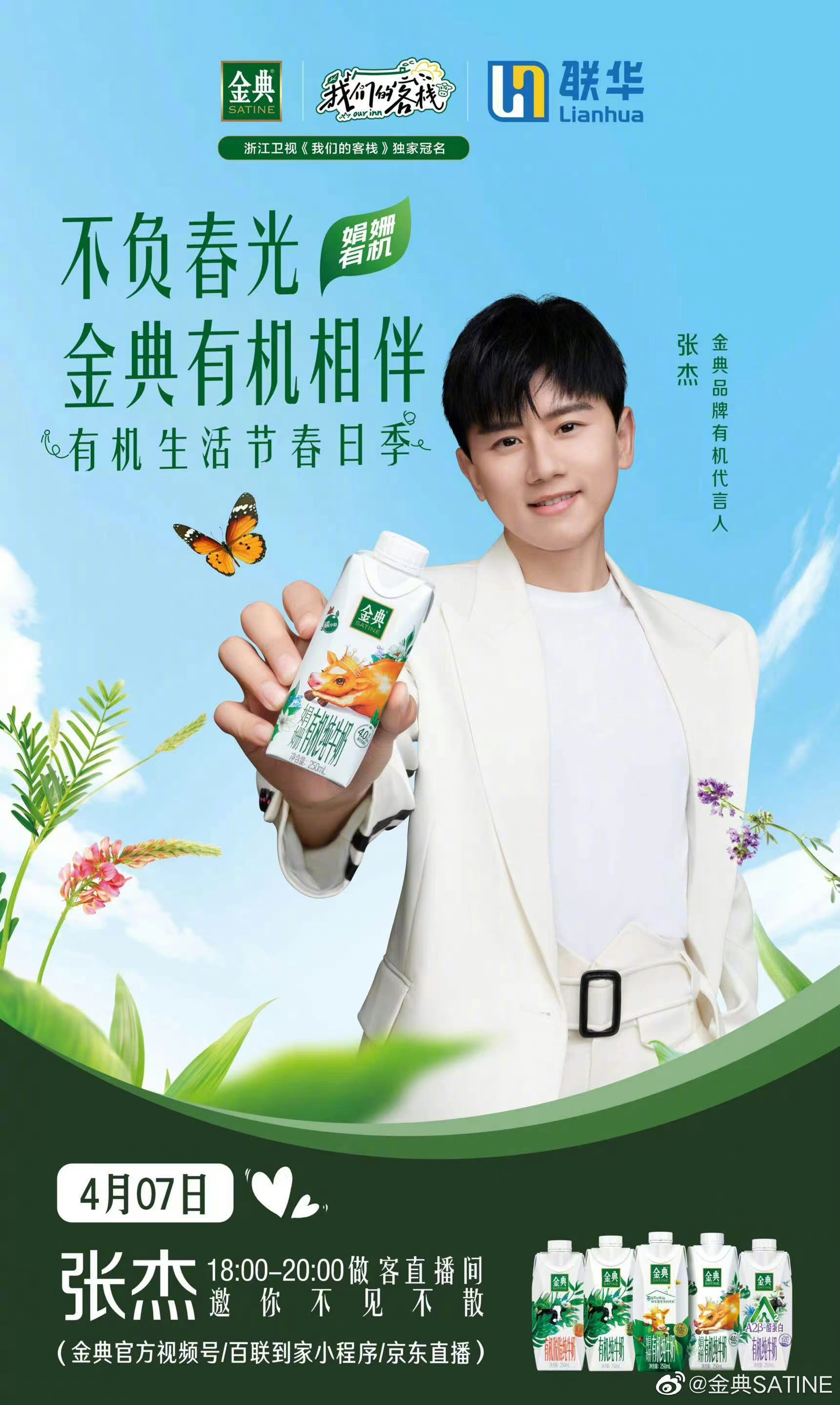
方正字迹-少壮体
罗源森
行楷、行书
“小书法家”罗源森,2004年生人,现年只有14岁。自幼酷爱书法,四岁起随父亲罗心海学习柳体《玄秘塔碑》、欧体《九成宫碑》和魏碑《等慈寺碑》,学前就打下了扎实的正书根基,六岁开始学习硬笔,八岁学习行书,被学校老师和同学们誉为“小书法家”。 作者在父亲的指导下,大胆运用毛笔柳体中的方刚果敢,魏碑中的沉劲雄浑,欧体中的险峻,王羲之《兰亭序》的行云流水,清秀飘逸,米芾书法中的险、绝、侧、倾的体势等风格,把这些妙法融合到硬笔行书当中,结合规范汉字的书写要求,创作出了这套硬笔书法字库。